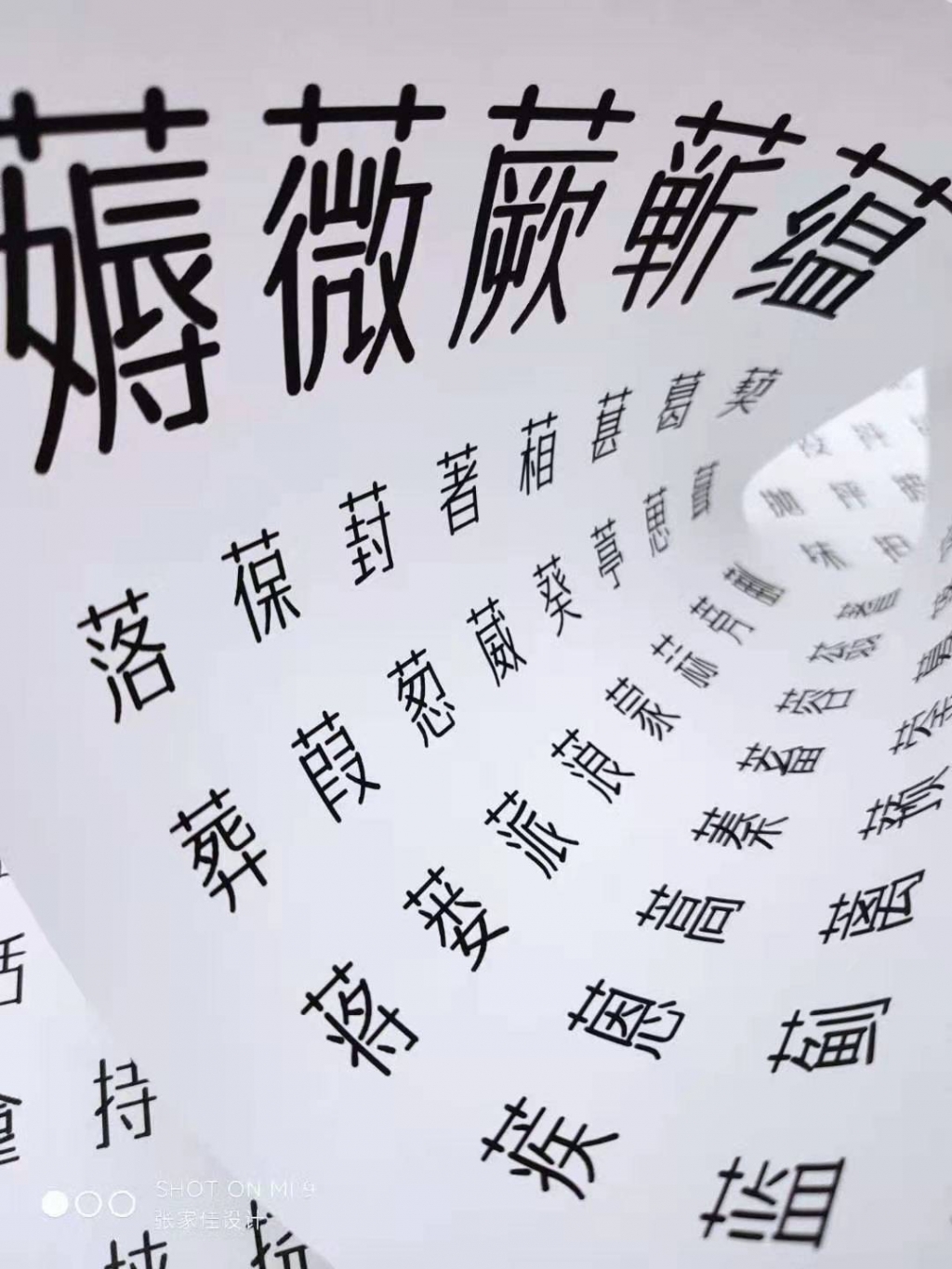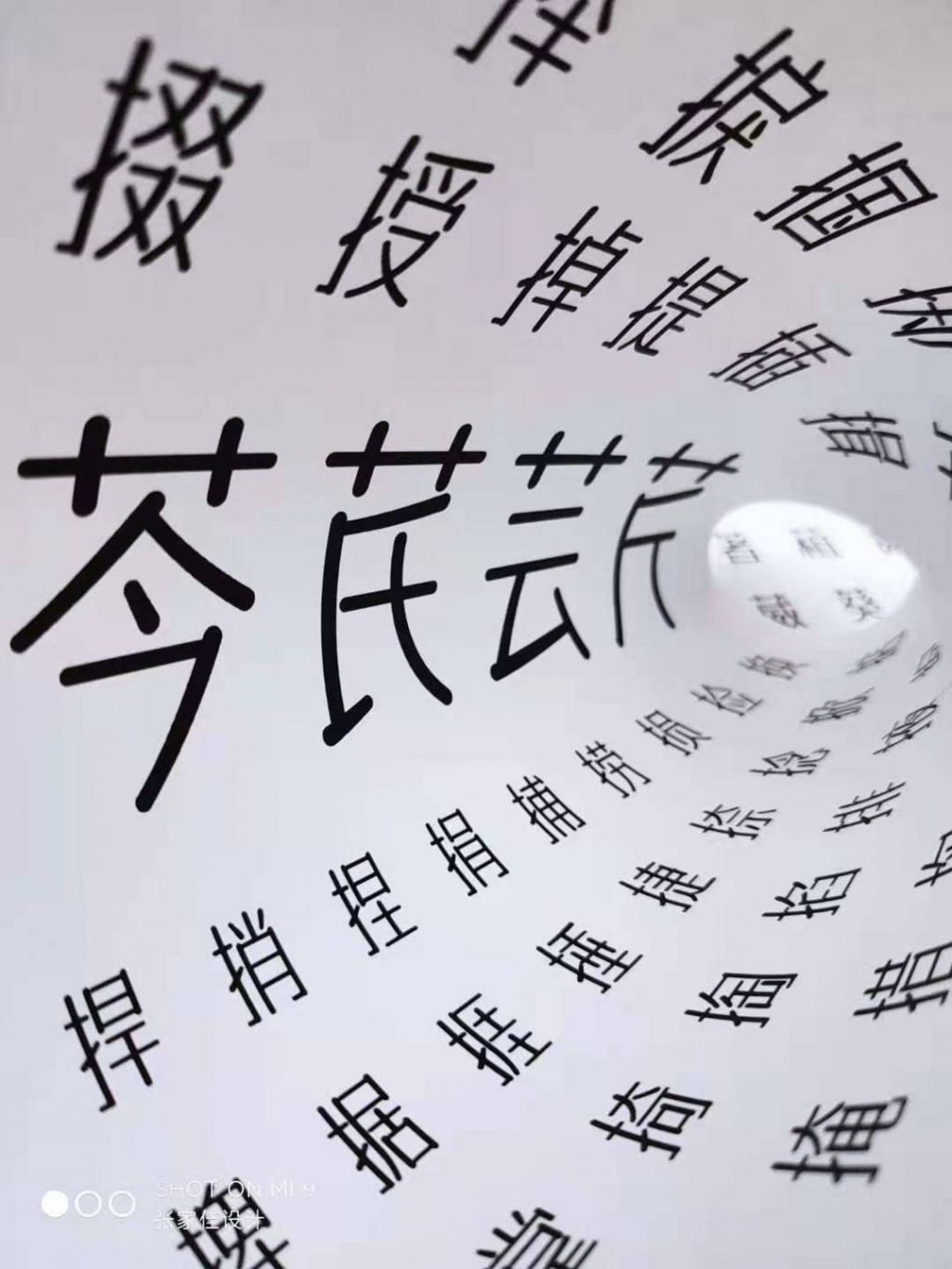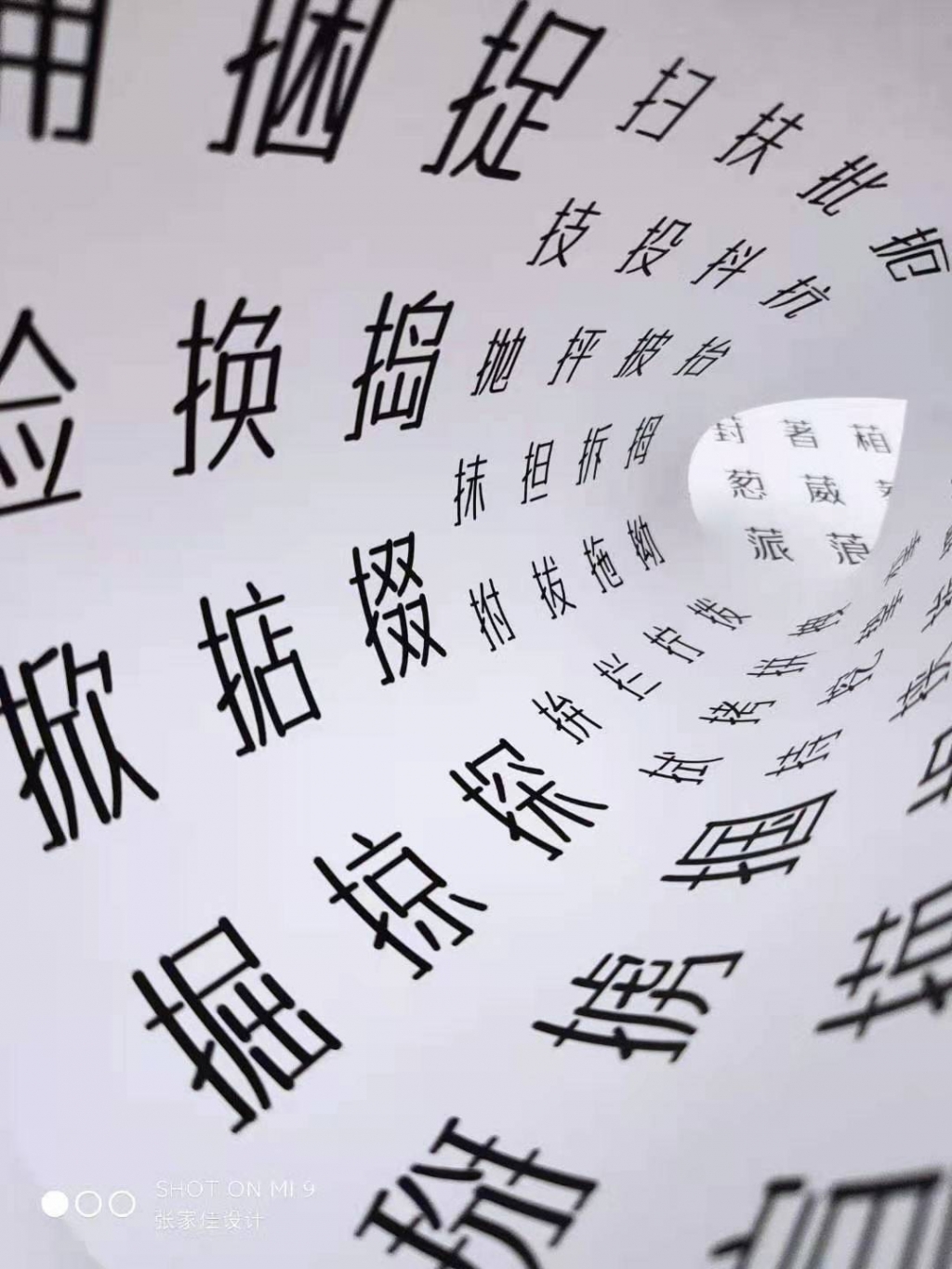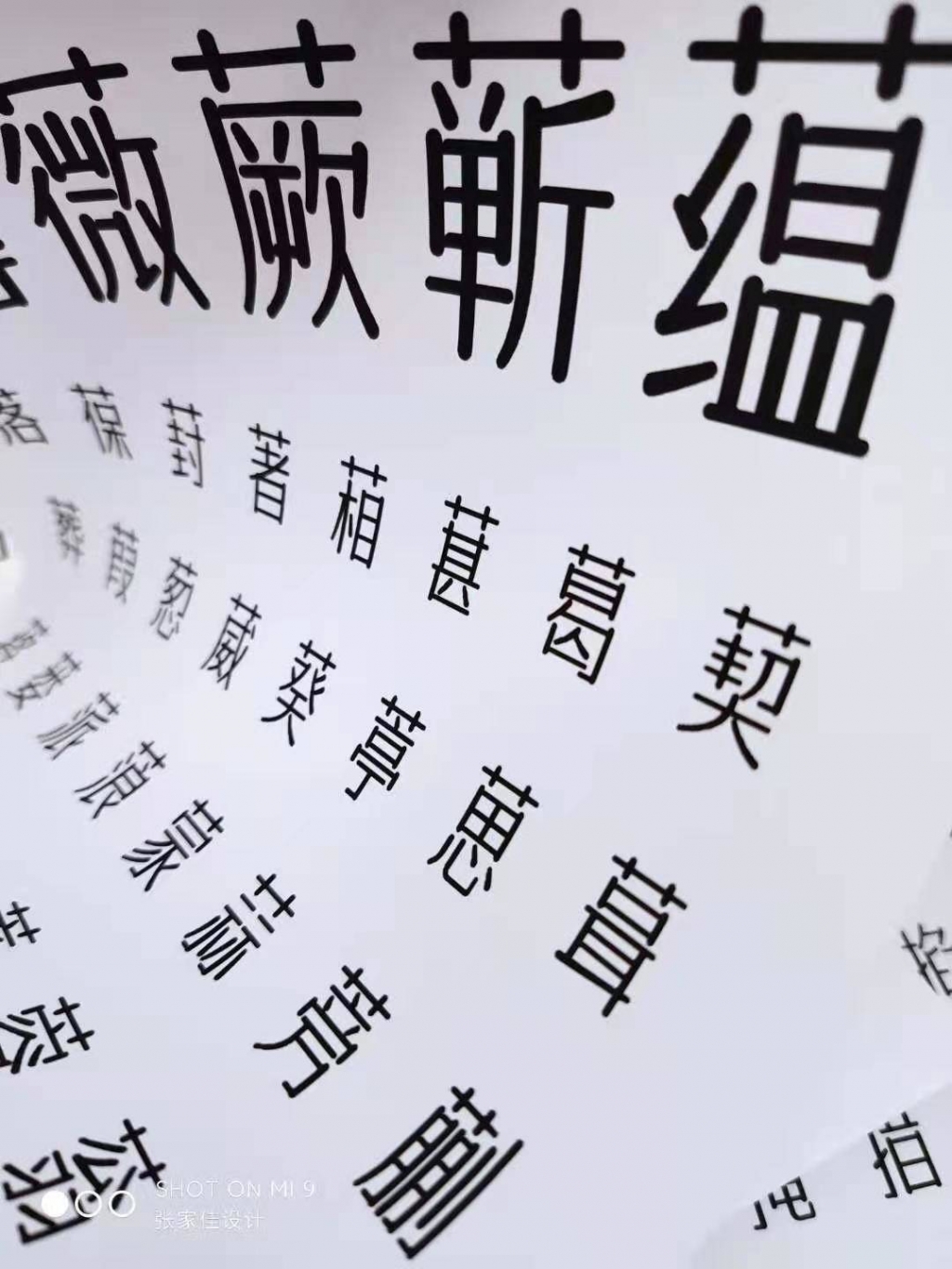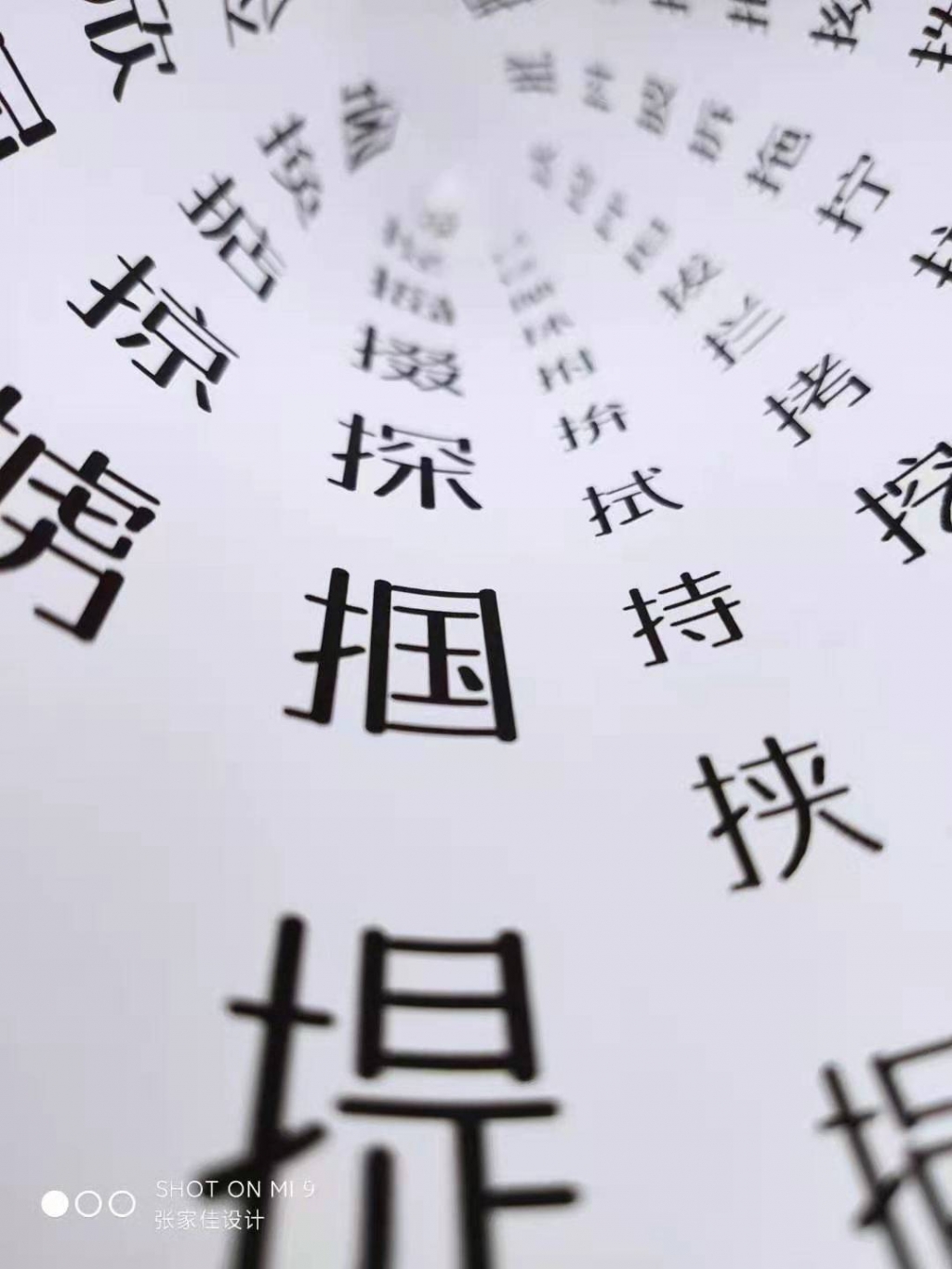
字体传奇:第二款免费商用公益字体即将上线 下周全球发布
今天还没有呢吗?很喜欢的字体
隔壁字库网已经出了
命名为南安体,之前哥特风格的南安体不见了,文章链接http://www.ziticq.com/Interview/11
• 现在还没有正式发布的吧?
• 上面链接中说下周三
作者很机智啊,把打印出来卷一下,拍张照,都不用做风格海报了,哈哈哈哈
• 确实机智,做海报费时间,有那时间还不如检查下文件或多做几个字,哈哈哈
初看与”优设好身体”有点类似
期待!
这款字体从昨天字体传奇公众号推广文章中的留言看,似乎字数达到3万,很有可能简繁通杀,如果真这样,那就是一款优质免费字体
圆体不错,现在圆体很少
真的好好看
看起来不错
期待
这个字不错。